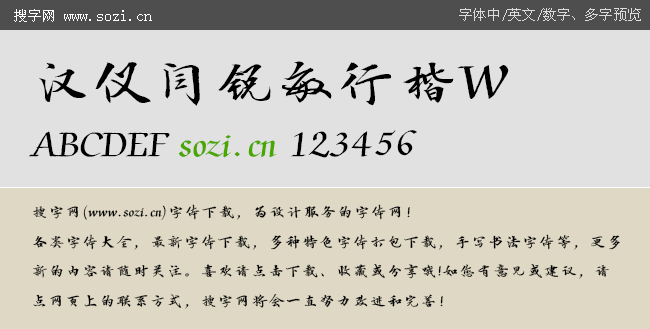
漢儀閆銳敏行楷W
搜字網(wǎng)提供一款漢儀閆銳敏行楷W中文書(shū)法字體下載,漢儀閆銳敏行楷是一款非常漂亮的手寫(xiě)風(fēng)格書(shū)法字體,字體端正大方,整體效果非常漂亮,適合應(yīng)用于廣告設(shè)計(jì)、名片設(shè)計(jì)、包裝印刷、海報(bào)設(shè)計(jì)等應(yīng)用。